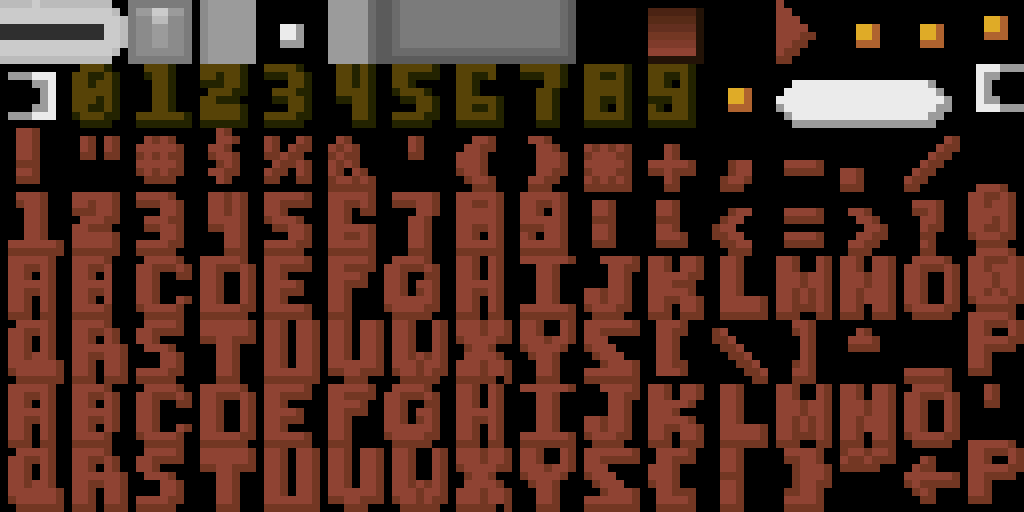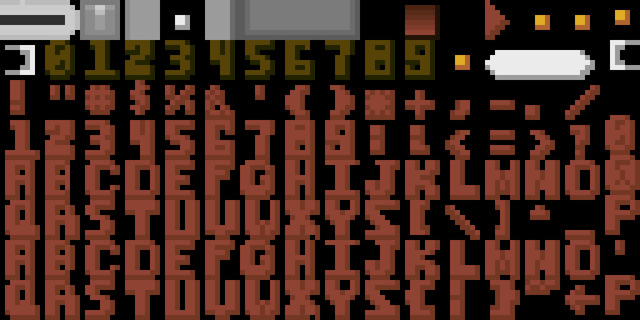
Пиксельный шрифт для вашей игры
Разработчиком Dreameater Games выложен для свободного скачивания по лицензиям BSD 2 и Creative Commons Attribution v4.0 International новый пиксельный шрифт, в т.ч. совместимый с Quake Engine. Это лист шрифта размером 8х8 (кернинг слева на 1 пиксель), а также отдельно все буквы.